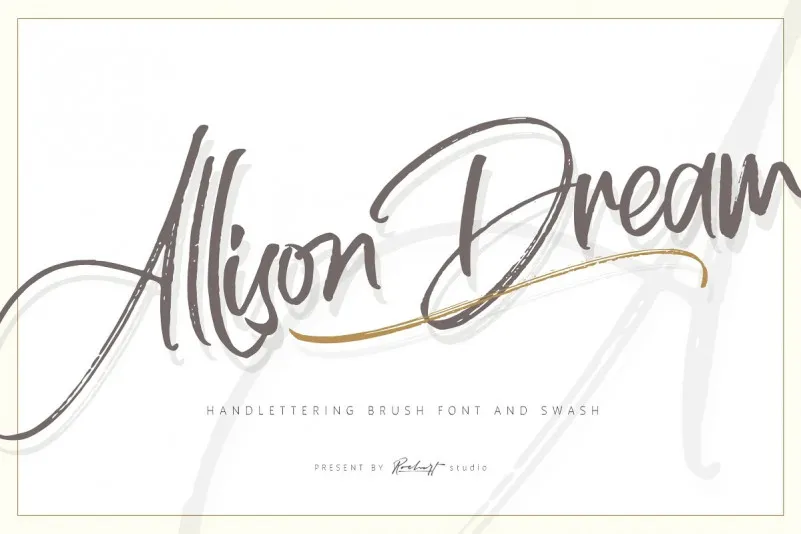
Allison Dream Font – Download Grátis
Esta é uma moderna fonte de escrita a mão natural feita com pincel. Rochart concebeu e compartilhou esta fonte Allison Dream para uso em logotípico, design de marca, design de logotipo, arte de letras digitais, camisetas/tênis, posters, revistas, sinalização, design publicitário, convites casamento e qualquer necessidade de escrita à mão. Esta fonte é perfeita para quando você precisa de uma letra a mão única ou seletiva. Com sua aparência natural e moderna, Allison Dream pode adaptar-se facilmente aos diversos campos onde suas letras criativas são sempre bem-vindas, desde um design simples até um projeto complexo. Seja para criar seu próximo selo da marca, fazer uma série de camisetas ou mesmo criar o plano de logotipo ideal, esta fonte oferece a você opções incríveis de personalização e flexibilidade no design.